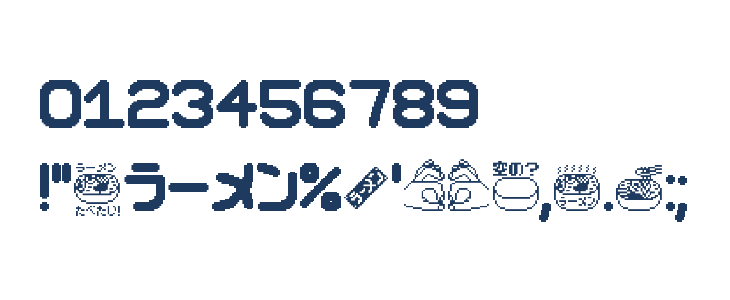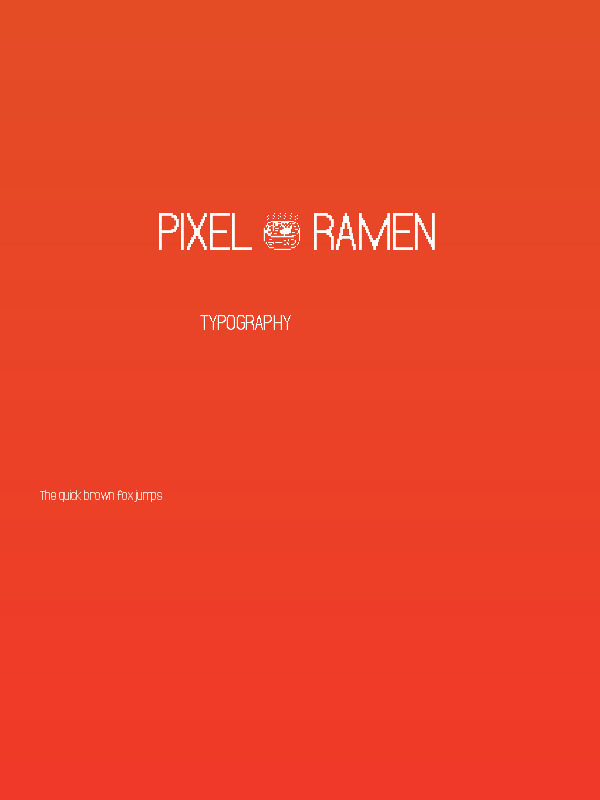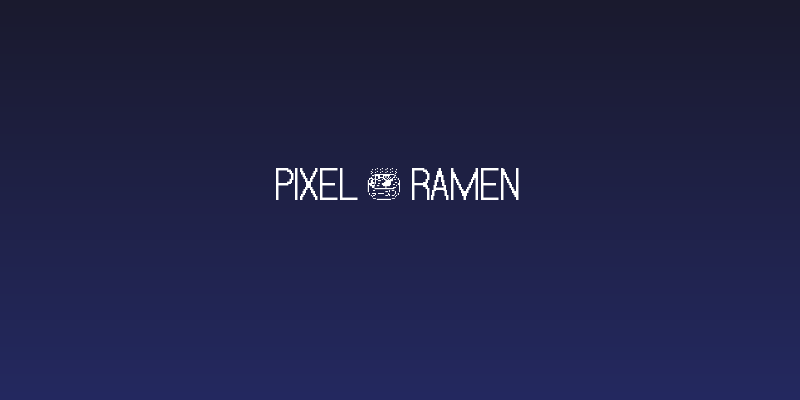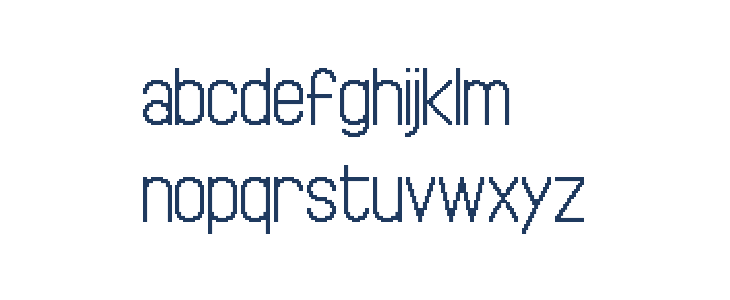
Pixel - Ramen Font
| Caso d'uso | Logos, Headlines, Digital Art |
| Progetti proposti | Ideal for video game design, retro-themed posters, digital art, and any project seeking a vintage digital look. |